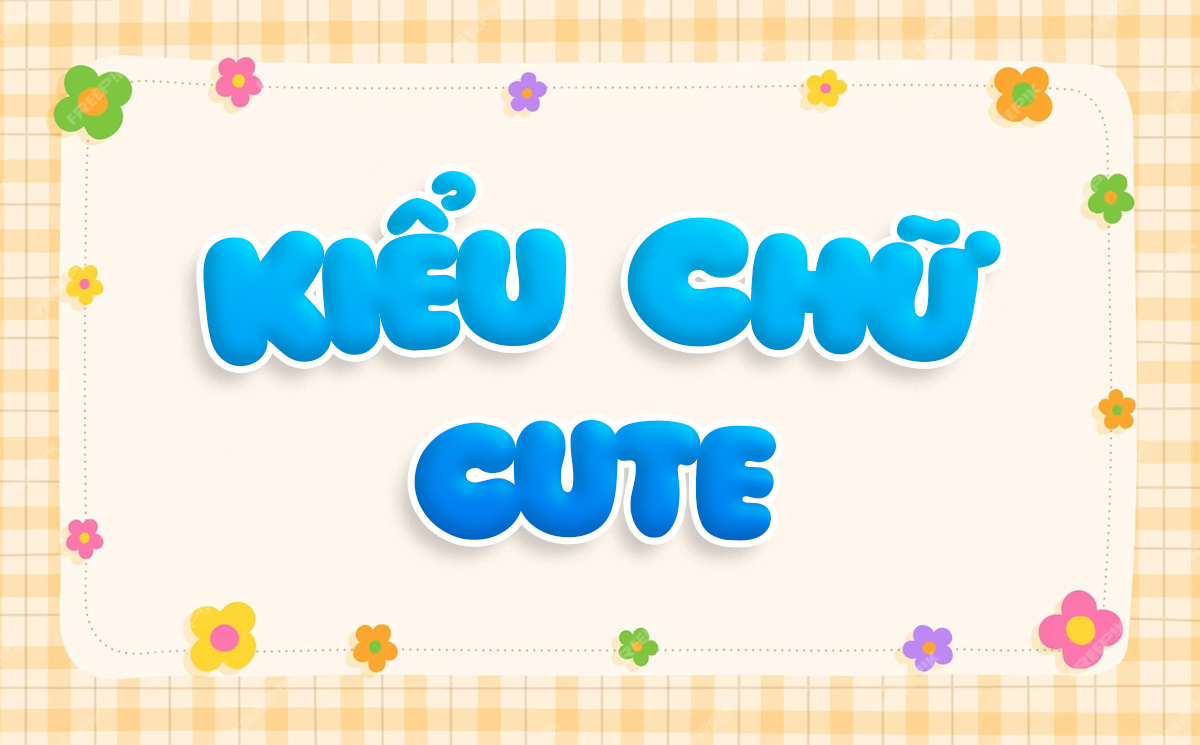
Download font chữ béo (hay còn gọi là phông chữ Chunky, Bubble hoặc Extra Bold) là nhu cầu hàng đầu của các designer khi cần tạo ra những tiêu đề bùng nổ, vui nhộn và cực kỳ thu hút thị giác. Với đặc trưng là nét chữ dày, mập mạp và vững chãi, phông chữ béo giúp tên thương hiệu trên bao bì nổi bật hoàn toàn giữa các sản phẩm khác. Doozypack.vn tổng hợp link tải font chữ béo trọn bộ đã được Việt hóa chỉn chu, giúp bạn tự do sáng tạo logo, banner và vỏ hộp sản phẩm mà không lo lỗi hiển thị dấu tiếng Việt.
Font chữ béo là gì? Tại sao nên ứng dụng vào thiết kế bao bì?
Font chữ béo không chỉ là những phông chữ được tăng độ đậm (Bold), mà là những bộ font được thiết kế riêng biệt với cấu trúc hình khối mập mạp, các góc bo tròn hoặc nét vẽ dày đặc trưng.
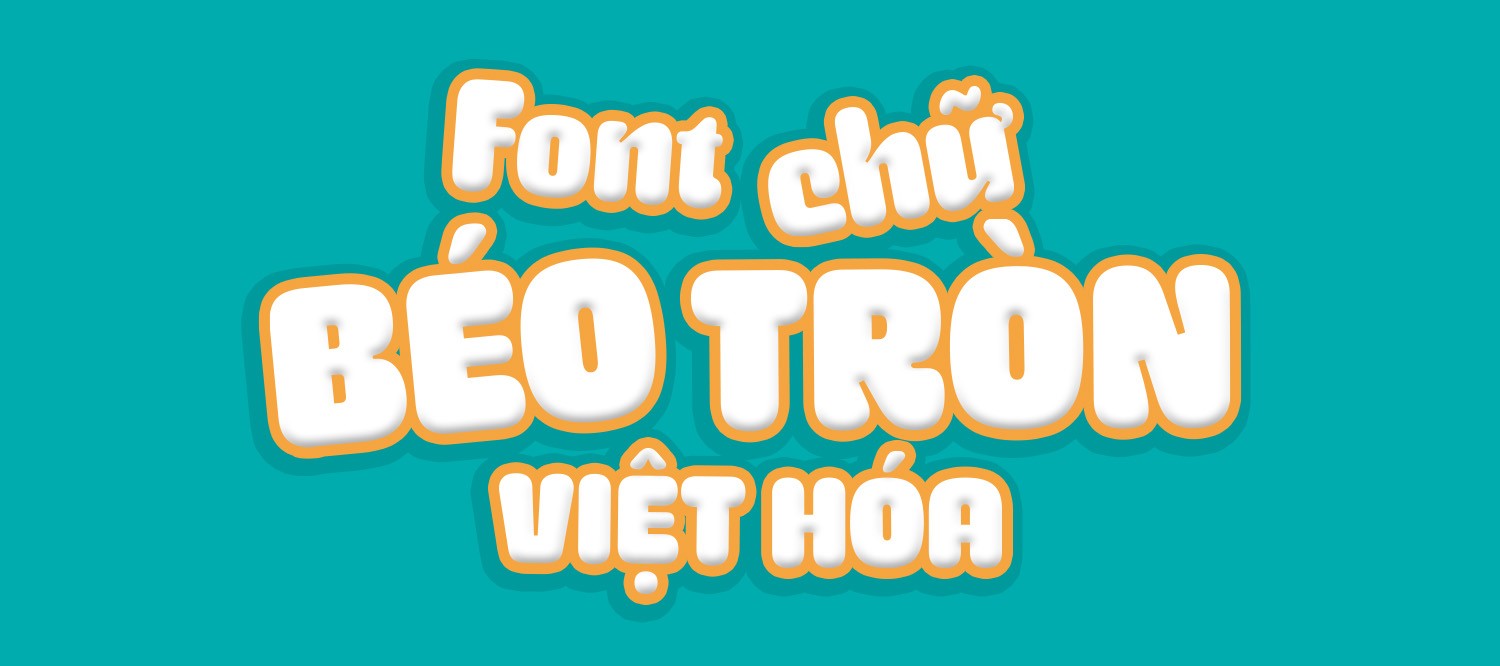
Khả năng thu hút thị giác tuyệt vời
Đặc trưng lớn nhất của font chữ béo là “sức nặng” về mặt thị giác. Khi khách hàng lướt qua kệ hàng, những dòng chữ dày dặn thường được mắt người nhận diện nhanh hơn các nét mảnh. Chính vì vậy, nhóm font này là “vũ khí” bí mật để làm tiêu đề chính trên nắp hộp quà tặng hoặc mặt trước của túi giấy, giúp truyền tải thông điệp thương hiệu một cách dứt khoát và mạnh mẽ.
Tạo cảm giác thân thiện và vui tươi
Hầu hết các bộ font chữ béo dòng Rounded hoặc Bubble mang lại cảm giác vô cùng gần gũi, năng động và tràn đầy năng lượng tích cực. Đối với các ngành hàng như thực phẩm, đồ chơi trẻ em hay mỹ phẩm handmade, phông chữ béo giúp xóa bỏ sự khô cứng, tạo thiện cảm và kích thích hành vi mua hàng của người tiêu dùng.
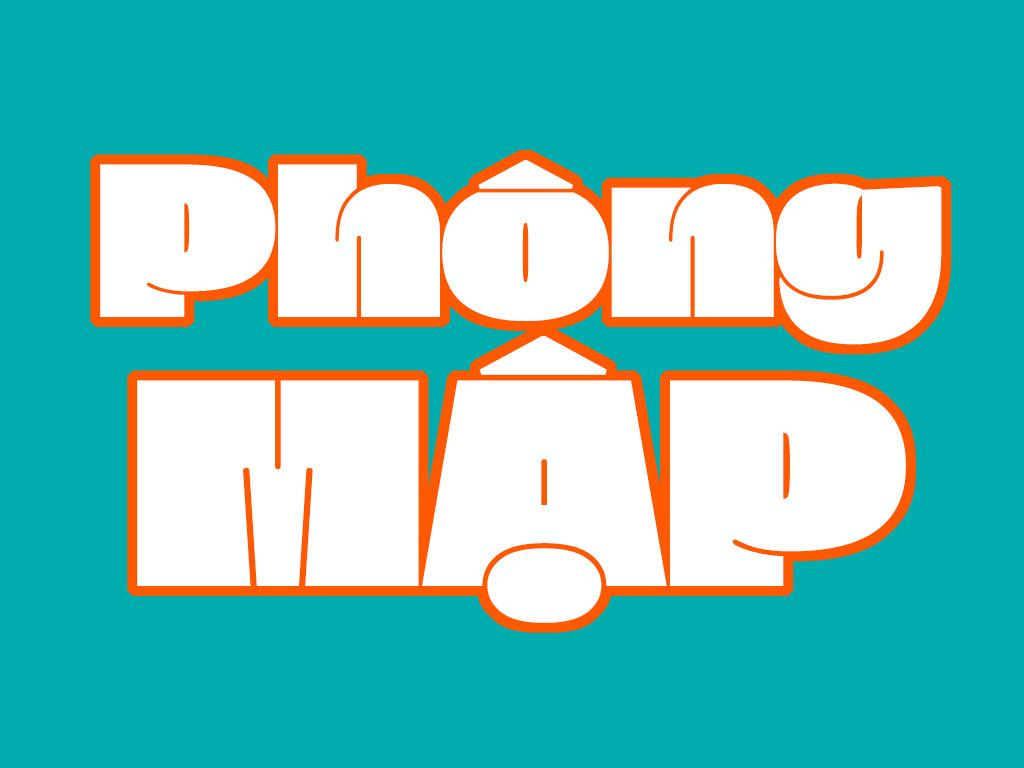
| Tên Font / Nhóm Font | Đặc điểm thị giác | Ứng dụng đề xuất tại Doozypack.vn |
| Font Bubble (Dạng bong bóng) | Tròn trịa, mập mạp, vui nhộn | Thiết kế bao bì bánh kẹo, đồ chơi, sản phẩm trẻ em. |
| Font Chunky (Dạng khối) | Vững chãi, mạnh mẽ, dứt khoát | Làm Logo Streetwear, poster sự kiện, túi giấy thời trang. |
| Font Display Extra Bold | Hiện đại, chuyên nghiệp | Tiêu đề hộp quà tặng doanh nghiệp, banner khuyến mãi. |
03 Ứng dụng của font chữ béo trong sản xuất bao bì thực tế
Sự độc đáo của các dòng phông chữ mập mạp mang lại hiệu quả thị giác đặc biệt trên các ấn phẩm tại Doozypack.vn:
- Hộp giấy thực phẩm (Bakery & Snack): Nét chữ béo gợi cảm giác đầy đặn và ngon miệng, rất hợp làm tiêu đề trên hộp bánh cookie, kẹo dẻo hoặc nhãn dán chai nước ép trái cây.
- Tem nhãn dán Sticker: Với hình khối chắc chắn, font chữ béo cực kỳ phù hợp để in các tem decal tròn hoặc tem niêm phong hộp hàng, giúp sản phẩm trông sinh động và trẻ trung hơn.
- Túi giấy thời trang Gen Z: Tên shop in bằng font chữ béo kết hợp màu sắc rực rỡ trên túi giấy cán màng mờ tạo phong cách năng động và phá cách.
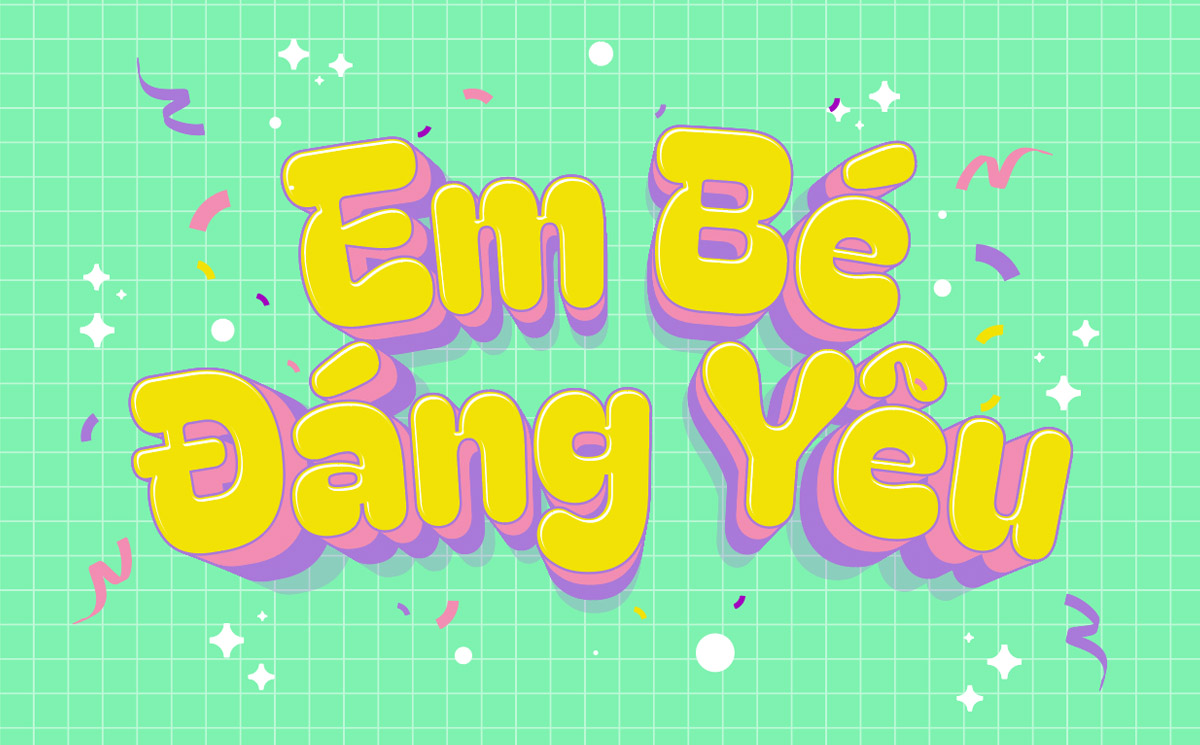
03 Lưu ý kỹ thuật khi in ấn font chữ béo
Sản xuất bao bì sử dụng phông chữ siêu đậm đòi hỏi designer cần lưu ý một số vấn đề kỹ thuật tại xưởng in chuyên nghiệp của Doozypack.vn:
- Kiểm soát hiện tượng Dot Gain (Tràn mực): Do các khe hở bên trong font chữ béo (như chữ ‘e’, ‘a’, ‘g’) thường rất nhỏ, khi in trên giấy có độ thấm mực cao, mực có thể bị lan làm bít kín các lỗ hở này. Bạn nên tăng nhẹ khoảng cách chữ (Tracking) để bản in thông thoáng.
- Cẩn trọng khi ép kim (Hot Stamping): Bề mặt chữ béo lớn tiêu tốn nhiều nhũ ép kim. Nếu diện tích ép quá rộng trên nền hộp mỏng, mặt giấy có thể bị cong vênh. Hãy yêu cầu kỹ thuật viên tư vấn định lượng giấy phù hợp trước khi làm khuôn.
- Quy tắc Convert Font: Để bản in không bị lỗi font hoặc nhảy dấu khi xưởng in mở file sản xuất, hãy luôn lệnh Create Outlines (Ctrl+Shift+O) trong AI trước khi gửi file PDF cuối cùng cho Doozypack.vn.